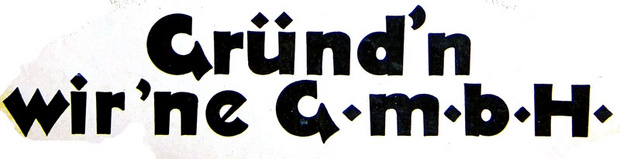
Schrift um 1930
Die Vorlage ist eine Handzeichnung, oder? Vermute ich jedenfalls, denn da ist ja kein Buchstabe wie der andere … Und Du suchst einen fertigen Font, um etwas ähnliches zu gestalten?
Die Neuland geht in die Richtung.
(wenn’s nur was ähnliches sein soll)
Schon mal sehr schön, vielen Dank. Gibt es vielleicht noch für das große G etwas ähnlicheres?
… Bausatz zusammen … :-)
Schlimmer als das Original kann’s ja nicht kommen :mrgreen:
Da würde sich auch die Abstrak eignen … weil ohne Gemeine nur für den Baukasten :-)
Mal so ne allgemeine Frage, ist es in so einem Fall nicht einfacher die Vorlage einzuscannen und 'ne Vektorgraphik draus zu machen, hat man da gestalterisch nicht ein sauberes Ergebnis als bei dem Baukastensystem? In der Zeit die ich damit verbringe die verschiedenen Fonts nach was passendem zu durchforsten hab ich das Ding doch drei mal vektorisiert.
Na klar wäre das einfacher. Ich gehe aber davon aus dass da noch mehr Text dazukommt, den es noch gar nicht gibt.
würde nicht auch eine Ashley Crawford passen?